Procreate Lettering Brushes
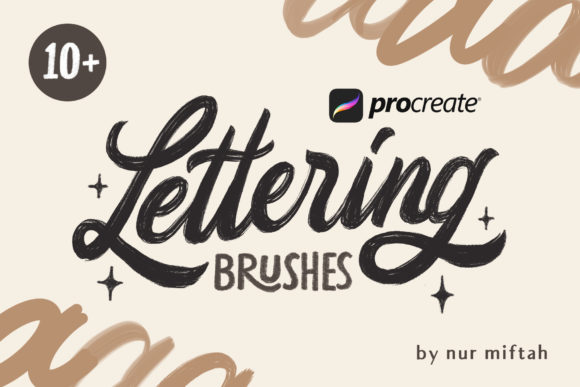
**Titre :** Renouvrez votre création avec les pinceaux de calligraphie Procreate Lettering Brushes
Si vous êtes amateur de création artistique, vous connaissez probablement l'application Procreate, célèbre pour son puissance et sa flexibilité. Pour améliorer votre expérience créative, nous vous proposons les Procreate Lettering Brushes, un ensemble de pinceaux de haute qualité destinés aux débutants, aux professionnels et aux créateurs de polices. Dans cet article, nous allons explorer les caractéristiques de ces pinceaux fantastiques et voir comment ils peuvent transformer votre travail.
- **10+ pinceaux de calligraphie** pour répondre à toutes vos besoins créatifs
- **Pinceaux texteurs** pour ajouter un peu de texture à vos créations
- **Pinceaux monoline** pour un style géométrique et minimaliste
- **Pinceaux de calligraphie** pour créer des polices et des textes élégants
- **Pinceaux de signature** pour ajouter un peu de personnalité à vos créations
- **Facile à utiliser** : les pinceaux de calligraphie Procreate sont conçus pour être faciles à utiliser, même pour les débutants.
- **Personnalisation** : chaque pinceau peut être personnalisé pour répondre à vos besoins spécifiques.
- **Flexibilité** : les pinceaux de calligraphie Procreate peuvent être utilisés pour une variété de styles et de techniques.
- **Débutants** : les pinceaux de calligraphie Procreate sont parfaits pour les débutants qui veulent améliorer leur style et leur technique.
- **Professionnels** : les pinceaux de calligraphie Procreate offrent une qualité et une précision pour les professionnels qui cherchent à améliorer leurs créations.
- **Créateurs de polices** : les pinceaux de calligraphie Procreate sont conçus pour les créateurs de polices qui veulent créer des polices élégantes et stylisées.
Les Procreate Lettering Brushes sont un ensemble de pinceaux de haute qualité qui peuvent transformer votre travail créatif. Avec leurs caractéristiques uniques et leur facilité d'utilisation, ils sont parfaits pour les débutants, les professionnels et les créateurs de polices. N'attendez plus pour renouveler votre création avec les Procreate Lettering Brushes !
Vous pouvez utiliser ces pinceaux dans l'application Procreate pour créer des créations uniques et personnaliser vos polices.
Les Procreate Lettering Brushes sont un ensemble de pinceaux de haute qualité conçus pour les débutants, les professionnels et les créateurs de polices. Ils offrent une facilité d'utilisation, une personnalisation et une flexibilité pour répondre à tous vos besoins créatifs.